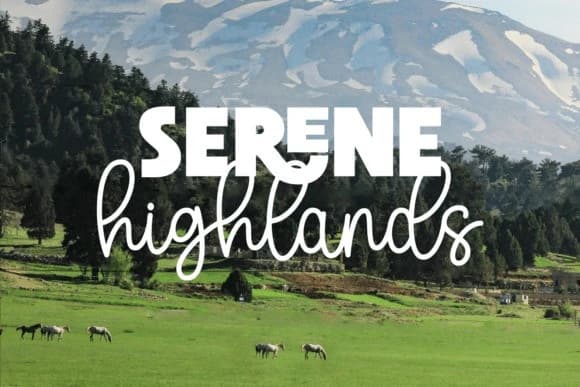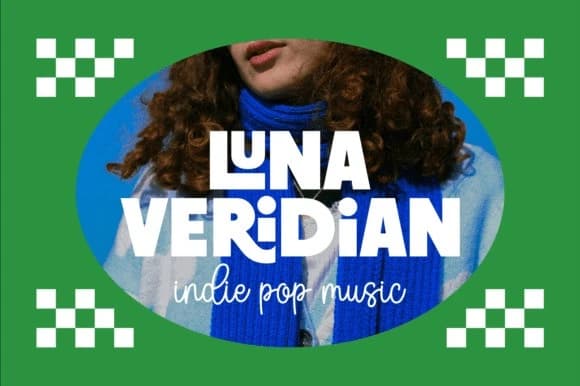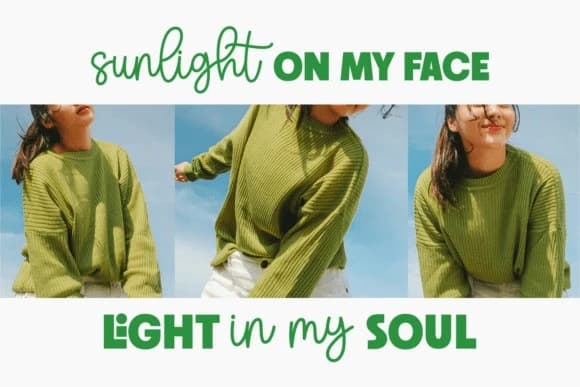
Güzel Caroline Yazı Tipi Çifti
Beautiful Caroline Font Duo: Oyuncu Zarafetin Uyumlu Bir Karışımı. Beautiful Caroline ile çekicilik ve modern tasarım arasındaki mükemmel dengeyi keşfedin; akıcı bir monoline el yazısını cesur, karakterlerle dolu bir display sans ile eşleyen premium bir font çifti.
Beautiful Caroline Font Duo Oyuncu Zarafetin Uyumlu Bir Karışımı. Beautiful Caroline ile çekiciliğin ve modern tasarımın mükemmel dengesini keşfedin; akışkan monoline script ile kalın, karakter dolu display sans'ı bir araya getiren premium bir Font Duo.